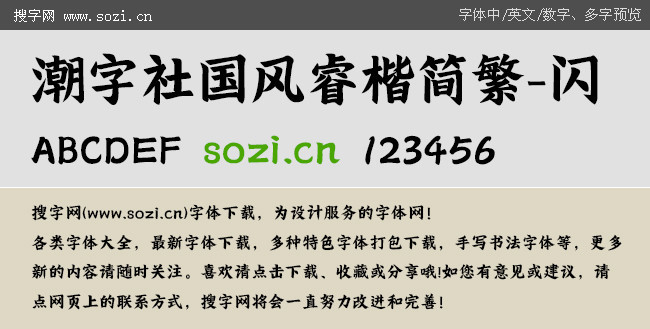
潮字社國風?喎-閃
搜字網(wǎng)提供一款潮字社國風?喎-閃中文字體下載,潮字社國風?喎笔且豢蠲P書法藝術字體,參考了古代書法楷書的結(jié)構(gòu)與筆畫形態(tài),融合了榜書正氣、學深的氣質(zhì)。字形流暢自然,渾厚有力,適合應用于藝術設計、平面宣傳設計、網(wǎng)頁設計等領域等應用。(本字體為個人非商用版,商用請聯(lián)系作者購買授權)